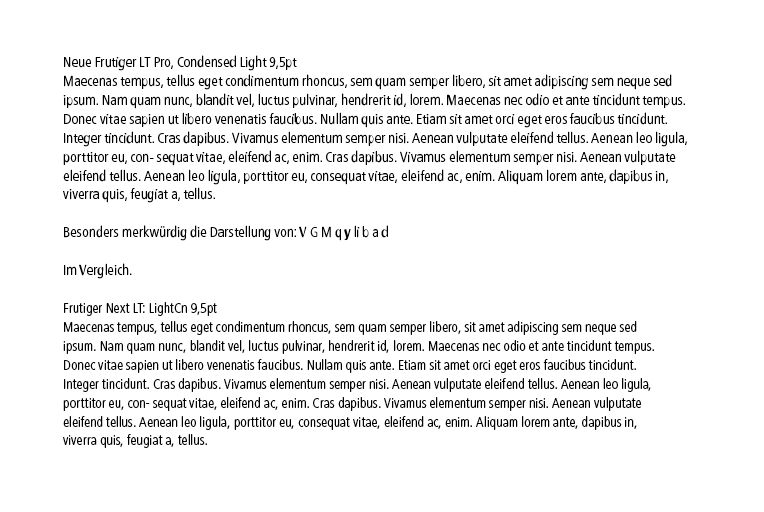
Darstellungsprobleme: Neue Frutiger
Problem:
Schrift: Neue Frutiger Condensed-Familie, ordnungsgemäß installiert.
In InDesign 6 und im Illustrator 6 zeigen sich Darstellungsprobleme (interessanterweise auch in den daraus exprotie rten PDF-Dateien), besonders deutlich im Mengensatz in 9,5pt aber auch bei größeren Graden,wenn man entsprechend zoomt. Der Eindruck der »angefressenen« Schrift geht erst in sehr hohen Zoom-stufen verloren.
Der Screenshot veranschaulicht das Problem und wurde in 100% aufgenommen.
In den »alten« Frutiger-Schnitten, (siehe Mustersatz unten) bzw in anderen Fonts taucht dieses Problem nicht auf.
Wer weiß hier Rat?
Hatte ich auch vermutet.
Aber wie kann das bei einer solchen Schrift und bei einem solchen Anbieter sein?
Wäre das ein Mangel, dessen Behebung man einfordern könnte.
Andere Schriften (auch die Vorgängerschrift) dieses Anbieters
weisen diesen Mangel ja nicht auf.
Was meinen Sie?
konntest du das Problem lösen bzw. liegt es tatsächlich am Hinting? Bei mir ist genau das gleiche Problem.